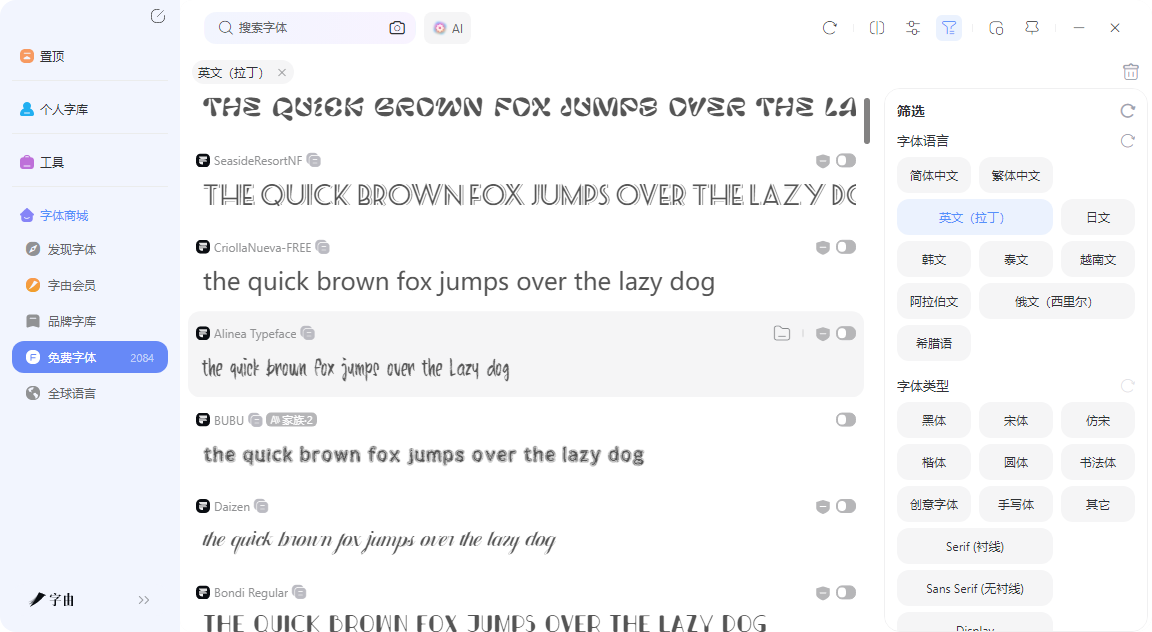
英文艺术字体不用愁,5个英文艺术字体网站推荐
做英文海报的时候,你有没有这种经历:脑子里大概有个方向,想要那种带艺术感的字体——比如笔刷手写、复古装饰、或者科幻风格。打开字体库翻来翻去就是那几款,怎么也找不到合适的。只能说市面上的、零散的字体资源质量确实有待斟酌,如果想避免这种情况,直接获得高质量的字体源的话,那么可以看我今天推荐的这5个网站,各有各的侧重,基本覆盖了从找字体到用字体的全流程。
字由(hellofont.cn)是一个集字体资源、管理与应用于一体的平台。注册用户超过2000万,收录了上万款字体。专门看英文字体的话,在客户端里筛选“英文(拉丁)”和“端庄优雅”的标签,目前有205款免费字体。这205款不是那种普通的Arial、Times New Roman,而是经过筛选的艺术风格英文字体。
怎么找到它们?打开字由客户端,在左侧筛选栏里选“英文(拉丁)”,然后在风格里勾“端庄优雅”“有趣”“手写风”“涂鸦”这些标签,就能看到大量适合做标题、Logo、海报的英文字体。
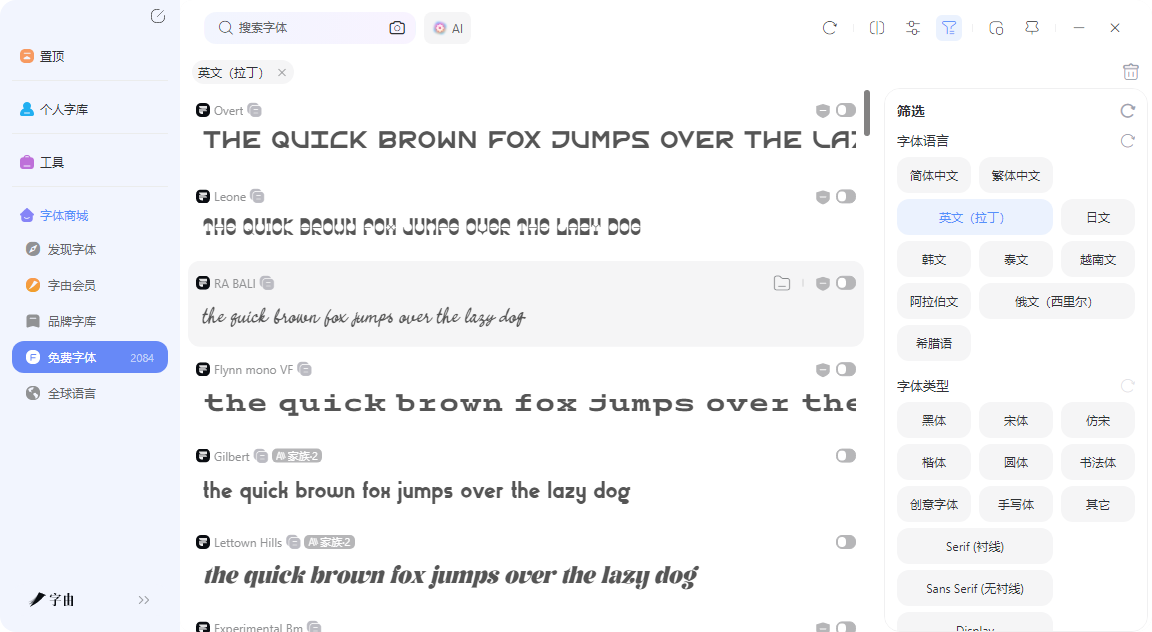
我比较推荐的字体有:
- LettownHills:一款优雅的英文字体家族,笔画流畅,适合做品牌标题。
- Daizen:日系风格的英文字体,字形偏瘦长,带禅意,适合东方美学设计。
- BRANIC:现代感强的无衬线体,干净利落,适合科技类海报。
- Wano Quin FR Thin:纤细优雅的字体,字重很细,适合女性化或高级感的设计。
- TheNightWatch:带有神秘感的字体,像守夜人的气质,适合暗黑风格。
- Alumni Sans:一个庞大的字体系列,有18种样式,从细到粗全覆盖。
- Bodoni Moda:经典衬线体Bodoni的现代版本,家族有74种样式,非常完整。
2、FONNTS
下一个要推荐的网站是FONNTS,它不是一个普通的字体下载站,而是一个按“艺术风格”来分类的字体库。打开首页,左侧有非常细的筛选栏。“Classification”这个分类下面,列了二十多种风格标签:SCI-FI(科幻)、LCD(液晶屏)、TECHNO(科技)、SQUARE(方形)、RETRO(复古)、3D、RUST(锈蚀)、STENCIL(模板字)、GROOVY( groove风格)……你想要的英文艺术字体,基本都能在这个分类里找到对应的标签。
页面上方有一段关于“Artistic Fonts 2026”的介绍,说这类字体以表现力和想象力著称,常常偏离传统的字母形状,加入抽象的、定制化的设计。每一款字体的造型都经过精心雕琢,整体呈现出独特的艺术气息。FONNTS还提供了“Quick Try”功能,输入文字可以实时预览效果。不需要注册,不需要付费,直接下载使用。不过下载前建议看一下授权说明,不是所有字体都免费商用。
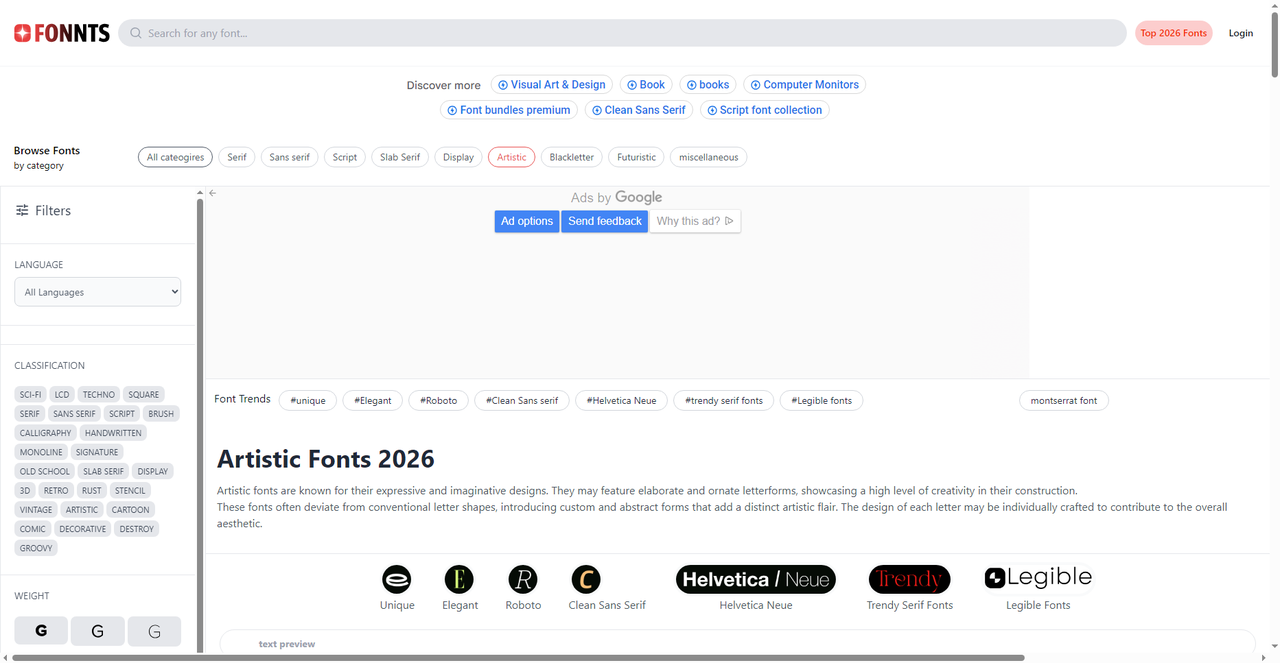
3、FreeFonts Vault
第三个网站叫FreeFonts Vault。它的“Art Fonts”页面专门收录艺术风格字体,而且每款字体都配有详细的设计背景介绍。
页面顶部有一段说明:艺术字体是为表达特定艺术风格或主题而设计的字体,常用于平面设计、广告、品牌项目。它们可能带有笔刷笔触、手绘插图、涂鸦元素等艺术装饰。流行的艺术字体风格包括书法、涂鸦、素描等。这个网站的优点是每款字体都写了详细的介绍和使用场景,不是那种只给个下载链接的粗糙站点。分类也很全,有Anime、Branding、Brush、Calligraphy、Cartoon、Glitch、Gothic、Handwritten、Horror、Logo等几十个类别。
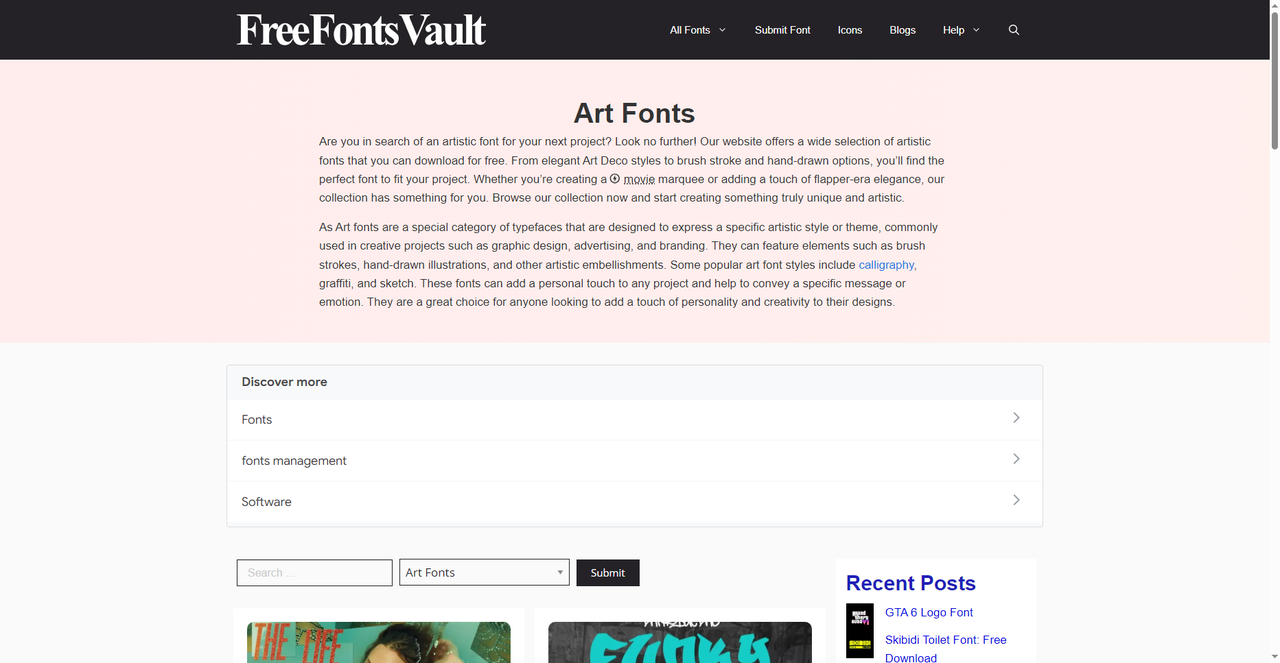
4、fontsisland
Fontsisland,它的“Art fonts”页面目前收录了1074款艺术字体,页面以网格形式展示字体预览图,每款字体都标注了下载量和查看量。比如“Ambassador”系列有33万下载,“Sony [Rus by me]”有20万下载,“Mrs Onion Monsters”有27万下载。这些数据能帮你快速判断哪些字体比较受欢迎。
Fontsisland的字体质量参差不齐,既有专业设计的精品,也有一些个人上传的习作。好处是数量多、风格全,你几乎不可能找不到想要的方向;坏处是需要花时间筛选。
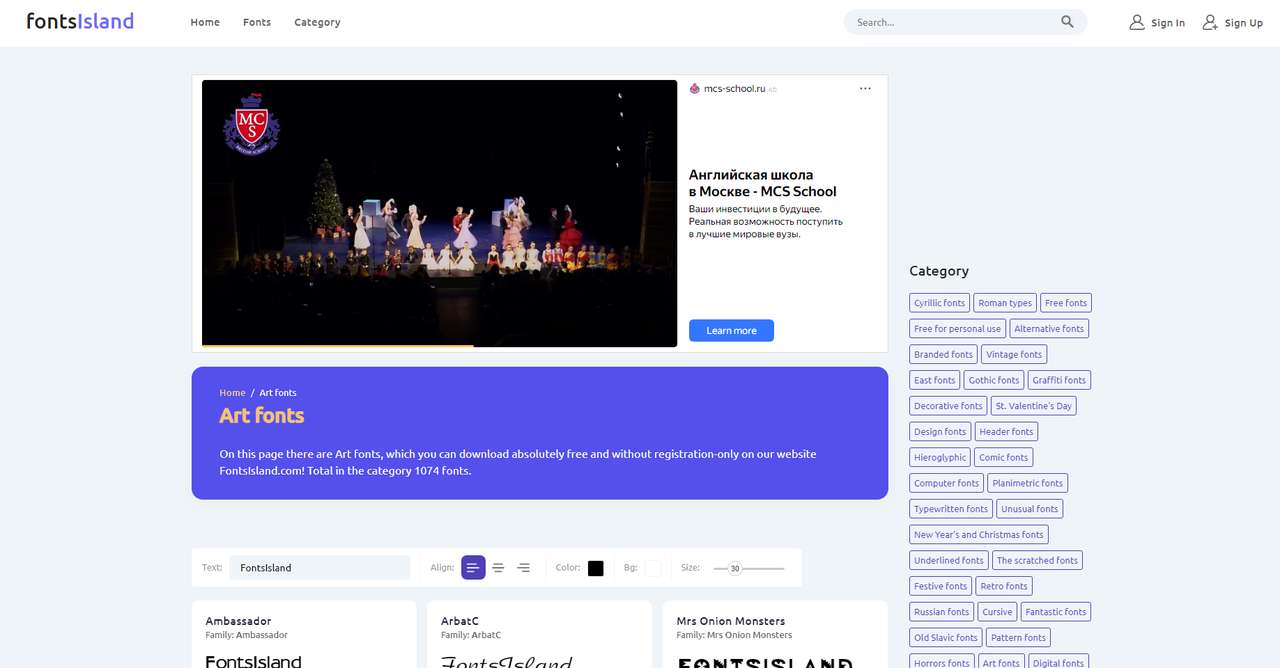
5、Artistic Fonts
第五个网站就叫Artistic Fonts,页面非常简洁。它不是那种带筛选功能的下载站,而是直接把15款艺术字体以图片形式列出来。每一款都配了预览图,点进去应该能看到更多信息和下载链接。
包括:Portrait Font、Norland Font、Beautiful Font、Aneliya Font、Aletcia Font、Agisthina Font、Artificial Intelligence Font、Zallman Caps Font、Fluid Font、Beloved Font、Symphonigraphy、Lavender、Alista Dotti、Agil Script、Alpha Danthe。
这个网站适合快速浏览,不用筛来筛去,直接看哪款顺眼就点进去下载。缺点是字体数量少,而且没有详细的分类和筛选。